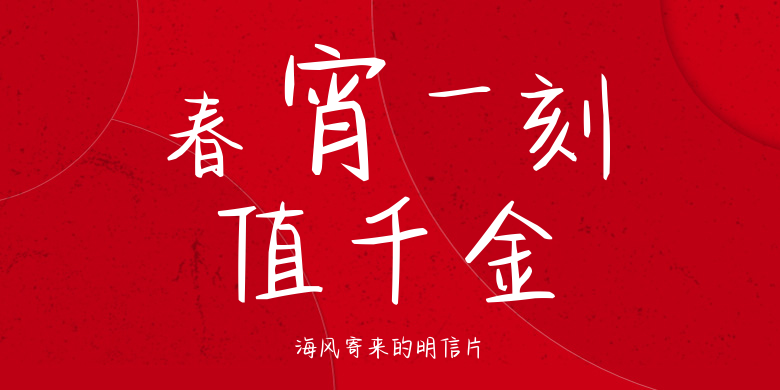
海风寄来的明信片
海风寄来的明信片,这款字体结构工整、笔画清晰,兼顾美观与易读性,适用于标题、正文、海报、包装、LOGO 等多种场景。字形优雅稳定,风格百搭耐看,适配日常排版与创意设计,让文字呈现更舒适、更具质感。海风寄来的明信片一笔一画,皆是细节,以均衡的比例、流畅的线条打造舒适视觉体验,字形端正大气,风格简约现代。无论是商业设计、品牌宣传还是日常排版,都能轻松驾驭,让文字更有格调与力量。海风寄来的明信片字体下载。